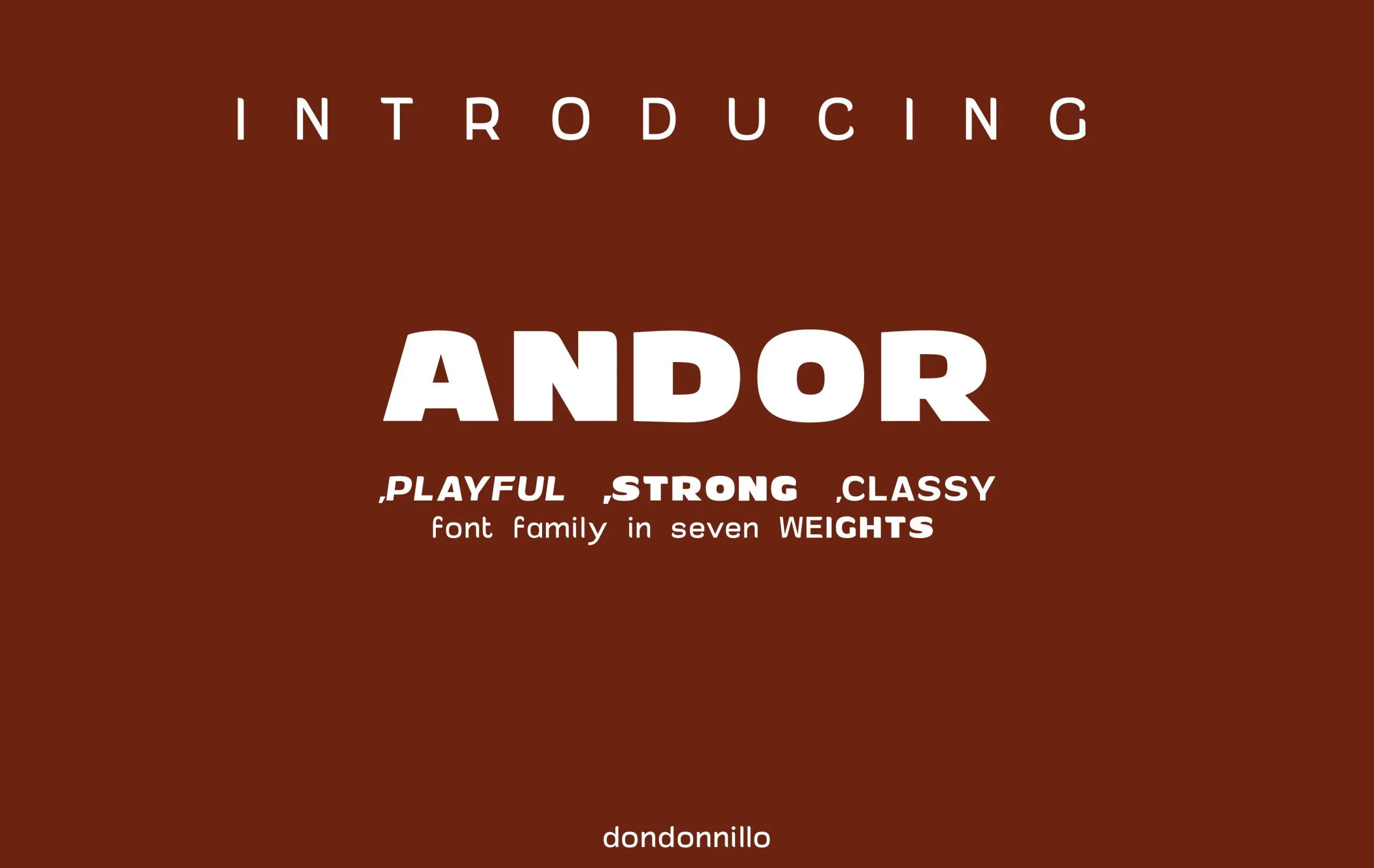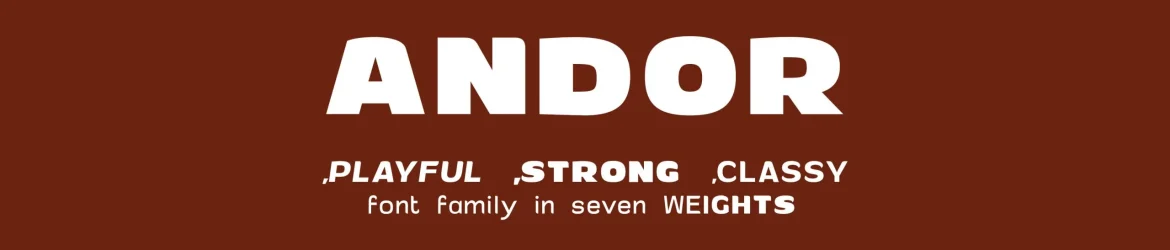
Andor Font é uma tipografia sans-serif cuidadosamente projetada por dondonnillo para atender uma gama diversificada de aplicações gráficas. Essa fonte versátil foi criada para satisfazer designers que buscam uma opção confiável e moderna, adequada a um amplo espectro de ambientes digitais, desde websites até logotipos e layouts de mídia social. Seja você um designer web atento às últimas tendências ou um estilista de moda buscando encontrar o próximo hit em sua nova coleção, Andor provavelmente tem uma versão que se adequará ao seu trabalho. Não importa o desafio gráfico pelo qual você esteja passando, a confiabilidade e simplicidade da Andor Font garantirão um resultado impecável sempre. Engaje-se no design moderno com Andor Font.